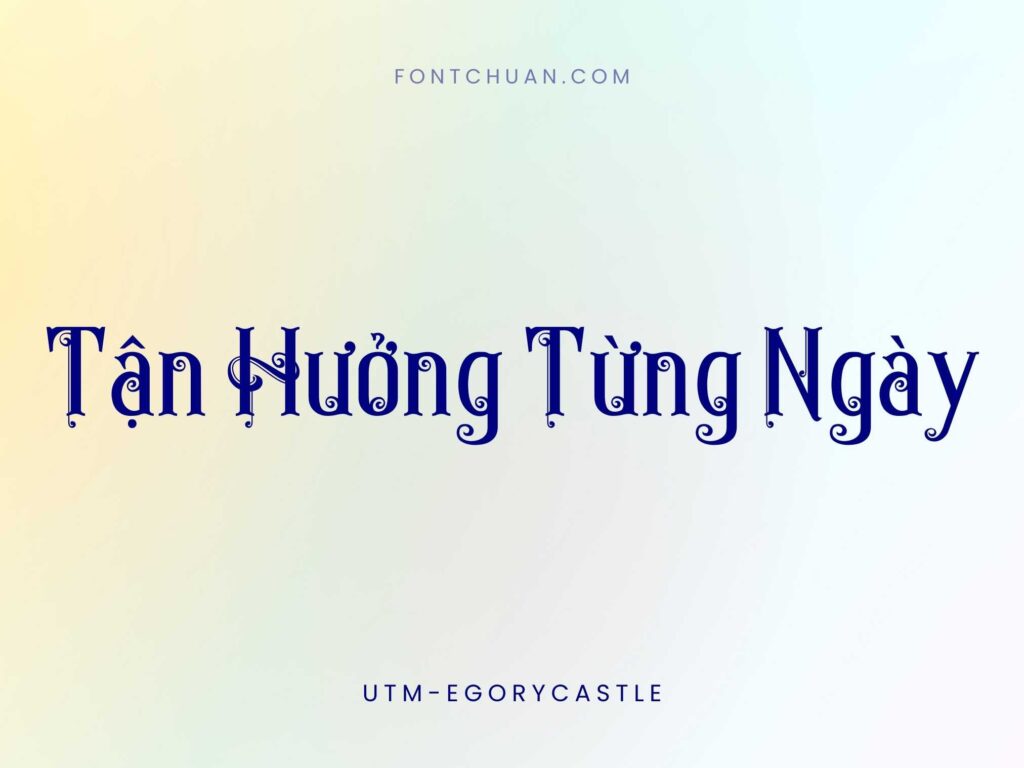
Font UTM Egorycastle Việt Hóa là một kiểu Font cổ trang, lấy cảm hứng từ những nét chữ truyền thống trong các bản thảo hoàng gia châu Âu. Với các đường nét hoa mỹ, kiểu dáng độc đáo mang vẻ huyền bí, font này phù hợp cho các thiết kế mang tính lịch sử, văn hóa và nghệ thuật cao cấp.
Font này đã được Việt hóa để hỗ trợ đầy đủ tiếng Việt bởi Thiên Minh, ngoài ra còn hỗ trợ hơn 200 ngôn ngữ khác. Thành viên của Font Chuẩn đã sưu tầm và chọn lọc font này nhằm đáp ứng nhu cầu của người dùng trong thiết kế và ứng dụng thực tế. Font có đặc điểm nổi bật với những nét chữ sắc sảo, phù hợp với các dự án như thiết kế poster, ấn phẩm văn hóa, bìa sách, và nhiều lĩnh vực khác.